인쇄 폰트 크기, 판형별로 직접 계산하는 워크시트
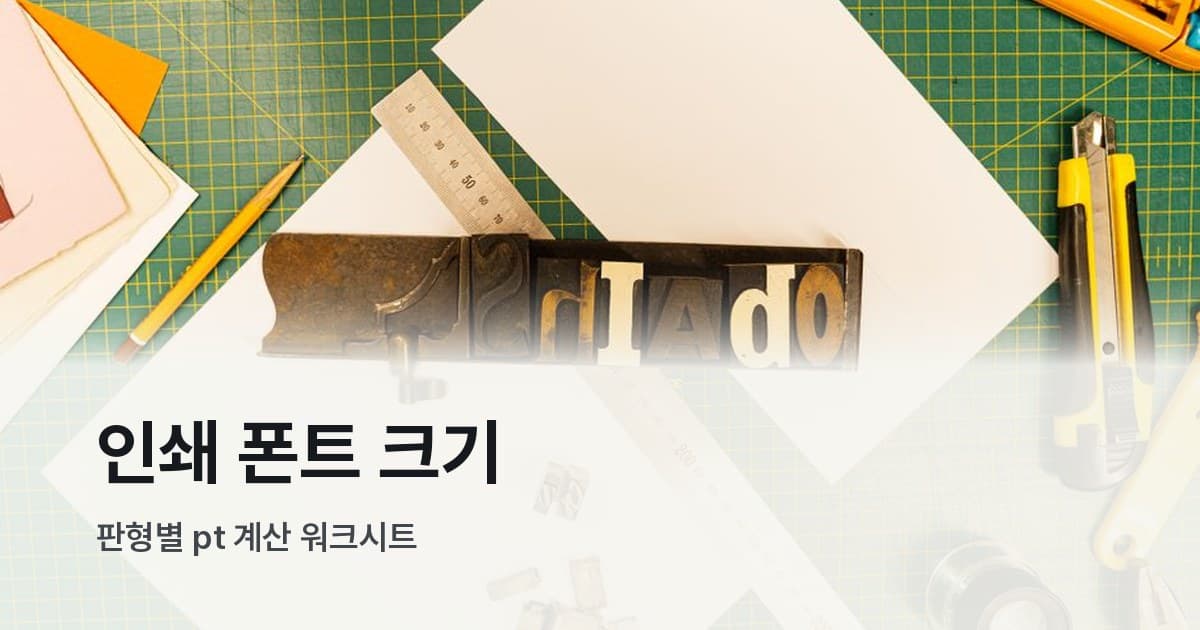
인쇄소에 파일을 넘겼다가 낭패 본 경험 있으신가요.
화면에서 멀쩡하게 보이던 글자가 막상 인쇄물로 받아보면 훨씬 작고, 어떤 건 아예 뭉개져 있고. 그래서 다시 수정하고 재출력하면 비용은 두 배. 제일 억울한 건 "폰트 크기는 10~12pt면 된다"는 말만 믿었는데 이런 일이 생긴다는 거예요.
사실 그 말이 틀린 건 아닌데, 명함이랑 A4 팸플릿이랑 복도 포스터가 전부 같은 pt를 쓰면 된다는 뜻은 절대 아니거든요. 인쇄 폰트 크기는 판형과 읽기 거리가 함께 결정합니다. 이 글에서는 그 원리를 짚고, 판형별 권장 pt 계산표와 읽기 거리를 직접 대입하는 5단계 절차를 함께 정리해드릴게요.
pt가 뭔지, 한 번만 짚고 넘어갈게요
화면에서는 px(픽셀)로 크기를 잡는데 인쇄 파일을 열면 pt, mm 같은 단위가 나오고 — 처음엔 이게 헷갈리죠.
pt(포인트)는 인쇄의 절대 단위예요. 1pt = 1/72인치 = 약 0.353mm. 소프트웨어가 바뀌어도, 출력 기기가 달라져도 이 물리적 크기는 고정입니다.
같은 pt인데 화면에서 보이는 크기가 다른 건 dpi(해상도) 때문이에요. 모니터는 보통 72~96dpi, 인쇄물은 최소 150dpi, 고품질 인쇄는 300dpi로 작업하거든요. 표로 보면 이렇습니다.
| DPI | 1pt의 픽셀 수 | 10pt의 픽셀 수 |
|---|---|---|
| 72dpi | 1px | 10px |
| 150dpi | 약 2.08px | 약 20.8px |
| 300dpi | 약 4.17px | 약 41.7px |
핵심은 이거예요. 화면 72dpi에서 16px로 보이던 글자를 300dpi 인쇄 파일에 그대로 16px로 넣으면, 물리적 크기로는 약 1.36mm밖에 안 됩니다. 거의 안 보이는 크기예요.
화면에서 px로 잡은 값을 인쇄용 pt로 착각하면 글자가 터무니없이 작아지는 게 이 이유입니다. 인쇄 파일은 항상 mm나 pt 단위로 설정하고, 해상도는 300dpi로 맞추는 게 기본이에요. A4 300dpi 파일이 약 2480×3508px인 이유도 여기서 나옵니다.
내 판형부터 찾고 시작하기
아래 표는 판형별 읽기 거리와 인쇄업계에서 통용되는 권장 pt 범위예요. 레드프린팅 가이드와 인쇄 실무 기준을 바탕으로 했습니다. 워크시트 시작 전에 내 판형 행을 먼저 찾아두세요. 뒤 Step에서 이 값을 기준점으로 씁니다.
| 판형 | 판형 크기 | 일반 읽기 거리 | 캡션 | 본문 | 소제목 | 제목 |
|---|---|---|---|---|---|---|
| 명함 | 90×50~54mm 내외 | 약 30cm | — | 7~9pt | 9~10pt | 10~12pt |
| A6(엽서) | 105×148mm | 30~35cm | 7pt | 9~10pt | 11~12pt | 14~18pt |
| A5(소책자) | 148×210mm | 30~40cm | 7~8pt | 9~10pt | 12~14pt | 18~24pt |
| A4(팸플릿·보고서) | 210×297mm | 40~50cm | 8pt | 10~11pt | 13~16pt | 24~36pt |
| A3(포스터 소형) | 297×420mm | 50~80cm | — | 12~14pt | 20~24pt | 36~60pt |
| A2·B1 이상(대형 포스터) | 420mm 이상 | 1~3m | — | — | — | 72pt~ |
표에서 한 가지 눈에 띄는 점이 있어요. 명함(30cm)의 본문 최솟값 7pt와 A4(50cm)의 10pt 사이가 읽기 거리 차이만큼 벌어지지 않는다는 것. 거리가 늘수록 글자 크기 자체보다 여백·행간의 역할이 커지고, 판형이 커지면 독자 눈이 한 번에 훑는 텍스트 블록 범위도 달라지기 때문이에요.
표를 쓸 때 주의할 실무 포인트 —
명함은 공간이 좁다 보니 연락처·직함·주소를 전부 넣으려다 7pt 미만으로 내려가는 경우가 많아요. 전문 인쇄소에서 작업해도 한글 7pt 미만은 획이 뭉개질 수 있습니다. 정보를 줄이거나 레이아웃을 단순화하는 게 낫고, 이름·직함은 10pt 이상, 연락처는 8~9pt 전후가 실제로 깔끔하게 나와요.
A5 소책자는 본문 9.8pt에 행간 20pt 조합이 가독성과 정보 밀도의 균형이 잘 맞는 것으로 알려져 있어요. 브런치 편집 디자인 사례에서도 자주 등장하는 조합이고, 한 줄 텍스트 프레임 폭이 약 82mm일 때 한 줄에 들어가는 글자 수와 호흡이 자연스럽게 맞습니다.
A4 단행본·보고서에서는 명조 계열은 9~10pt, 고딕 계열은 8~9pt가 실무 표준이에요. 고딕이 같은 pt에서 명조보다 조금 크게 느껴지는 특성이 있어서, 동일한 가독성을 내려면 고딕을 약간 작게 써도 돼요.
내 판형이 표에 없을 때 쓰는 워크시트 ✍
현수막·배너·전시 패널·입간판처럼 표에 없는 판형이거나, 표의 수치가 내 상황과 정확히 맞지 않을 때 직접 계산합니다. 아래 Step을 순서대로 따라가면서 [ ] 칸에 내 값을 채워 넣으세요.
기본 원칙: 읽기 거리가 1m 늘어날 때마다 글자 높이를 약 25mm(약 71pt) 크게 잡습니다. 포스터·사이니지 타이포그래피에서 경험적으로 쓰이는 공식이에요.
Step 1 — 독자가 이 인쇄물을 얼마나 멀리서 읽나요?
아래에서 내 환경을 고르거나, 직접 거리를 측정해서 적으세요.
| 판형/환경 | 읽기 거리 |
|---|---|
| 명함·소책자·잡지 | 0.3m |
| A4 팸플릿·브로셔 | 0.4~0.5m |
| 벽면 A3 포스터 | 0.5~1m |
| 복도 현수막·대형 포스터 | 1~5m |
| 도로변 대형 현수막·야외 간판 | 5m 이상 |
내 읽기 거리 = [ ] m
Step 2 — 제목에 필요한 최소 글자 높이를 계산합니다
최소 글자 높이(mm) = 읽기 거리(m) × 25
최소 pt = 최소 글자 높이(mm) × 2.835
내 계산: [ ] m × 25 = [ ] mm × 2.835 = [ ] pt
이 값이 제목의 최솟값입니다. 여유를 주고 싶다면 여기에 1.5를 곱하세요.
Step 3 — 계층 비율로 소제목·본문 pt를 구합니다
실무에서 자주 쓰는 비율은 제목:소제목:본문 = 약 3:2:1이에요. 정확한 배수보다는 계층이 눈에 들어오는지가 중요합니다. 제목과 소제목 차이가 2pt밖에 안 나면 독자 눈에 구분이 잘 안 돼요.
소제목 = 제목 pt ÷ 1.5 (약 2/3)
본문 = 제목 pt ÷ 3 (약 1/3)
내 계산:
- 제목: [ ] pt
- 소제목: [ ] pt ÷ 1.5 = [ ] pt
- 본문: [ ] pt ÷ 3 = [ ] pt
Step 4 — 공식으로 실제 사례를 검산해봅니다
복도 포스터(읽기 거리 2m)를 이 공식에 넣으면: 2 × 25 = 50mm → 50 × 2.835 ≈ 142pt. 이게 제목의 최솟값이에요. 본문 설명 텍스트는 이 값의 1/3인 약 47pt 이상인데, 계산상 최솟값이라 실제 포스터 본문은 24~36pt로 줄이는 경우가 많아요.
A3 포스터(관람 거리 0.8m) 예시:
- 최소 글자 높이 = 0.8 × 25 = 20mm
- pt 환산 = 20 × 2.835 ≈ 57pt
- 제목: 57pt 이상 / 소제목: 약 38pt / 본문 설명: 약 20pt
앞서 참조표에서 A3 제목 권장 범위가 36~60pt라고 했는데, 공식 결과값 57pt와 거의 맞아떨어지죠. 표의 수치가 이 원칙에서 도출된 것이기 때문이에요. 공식을 직접 써보면 "왜 A3 제목이 최소 36pt인가"가 자연스럽게 납득이 가요.
Step 5 — 최종 폰트를 놓고 1~2pt 미세 조정합니다
같은 pt라도 폰트마다 실제로 보이는 크기가 다릅니다. x-height가 큰 폰트는 더 크게 느껴지고, 세필 계열이나 장식 서체는 더 작게 느껴져요. Step 3까지 나온 값은 시작점이고, 최종 폰트를 놓고 실제로 출력 테스트해서 1~2pt 조정하는 게 마지막 단계예요.
출력 전 체크: 선택한 폰트로 100% 크기 PDF 출력 → 자를 대고 실제 글자 높이 측정 → Step 2 계산값과 비교
한글 폰트는 인쇄 폰트 크기를 조금 더 올려야 한다
영문 타이포그래피 기준에서 인쇄 본문 최솟값은 6~8pt예요. 그런데 한글은 얘기가 다릅니다.
서양 알파벳은 소문자 'x'의 높이(x-height)가 전체 폰트 크기의 약 0.4~0.55 수준인데, 한글은 초성·중성·종성이 한 음절 안에 다 들어가는 구조라 실질적인 글자 높이 비율이 0.7 이상이에요. 같은 pt에서 눈에 보이는 높이는 한글이 더 크게 나오지만, 그만큼 획 수와 복잡도가 훨씬 높기 때문에 작아지면 획이 뭉개지기 쉽습니다.
국내 타이포그래피 연구(독서 거리 30~35cm 기준)에서는 한글 본문 8~14pt를 권장하고, 가독성이 가장 안정되는 구간은 10~12pt예요. 영문보다 한 단계 올라간 수치고, 고령자 대상 연구에서는 12~13pt가 최적으로 나타나기도 했습니다.
행간도 빠뜨리면 안 돼요. 한글은 자모 높이 비율이 커서 행간이 좁으면 줄이 겹쳐 보이기 쉽거든요. 본문 폰트 크기의 1.2~1.5배를 출발점으로 삼고, 실무에서는 여유를 줘서 10pt 본문에 행간 20pt 전후로 설정하는 경우도 많습니다.
가정용 프린터나 복사 출력처럼 인쇄 품질이 낮은 환경에서는 8pt 이하 한글이 뭉개질 수 있어요. 전문 인쇄소라도 한글 7pt 미만은 위험 구간으로 봅니다.
폰트 고를 때 인쇄 허용 범위도 함께 확인하세요
pt와 행간을 잘 잡았어도 폰트 선택이 마지막 퍼즐이에요.
인쇄 폰트 크기 계산은 한 번만 원리를 잡아두면 어떤 판형이든 응용할 수 있어요. "왜 이 pt인가"를 설명할 수 있어야 클라이언트 수정 요청도 근거 있게 막을 수 있고요. 다음번 인쇄물 작업 전에 Step 1부터 차례로 내 값을 채워보세요. 인쇄소에서 돌아온 결과물이 달라질 거예요.